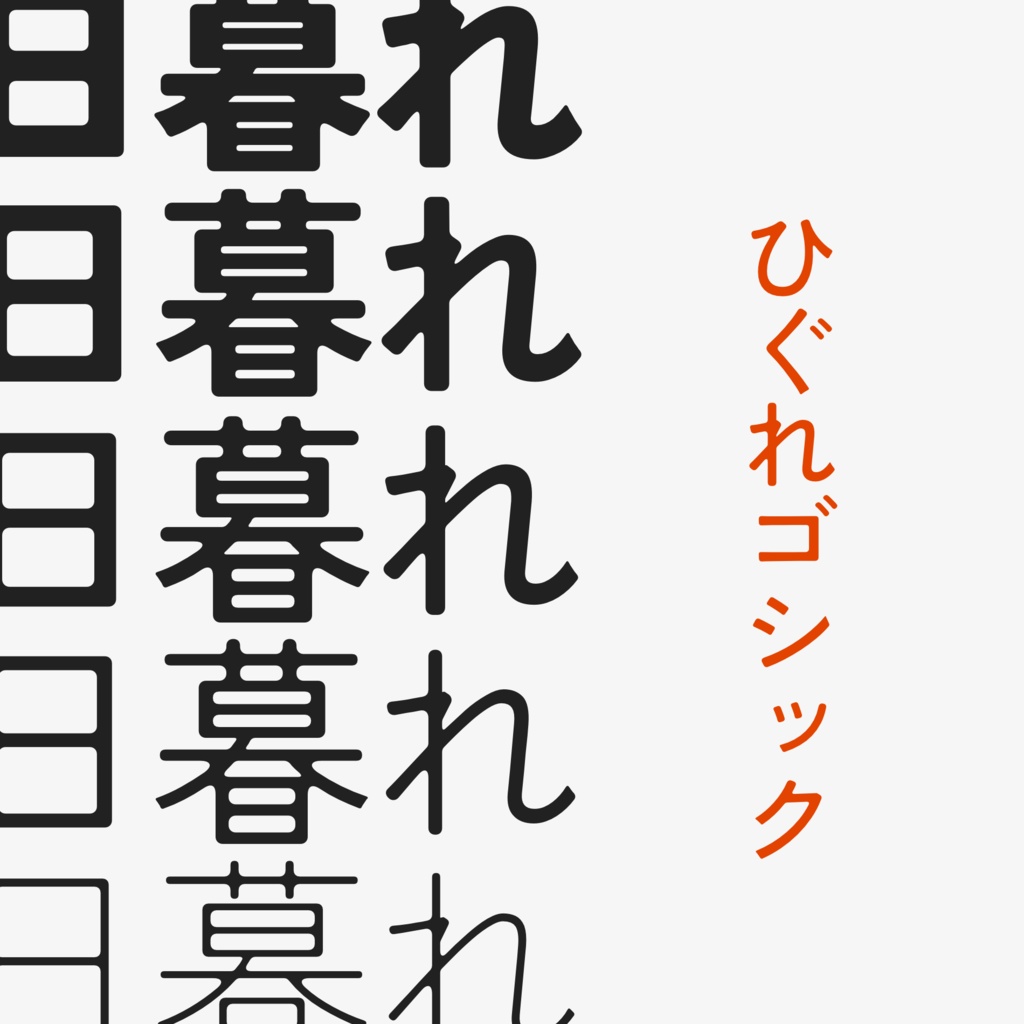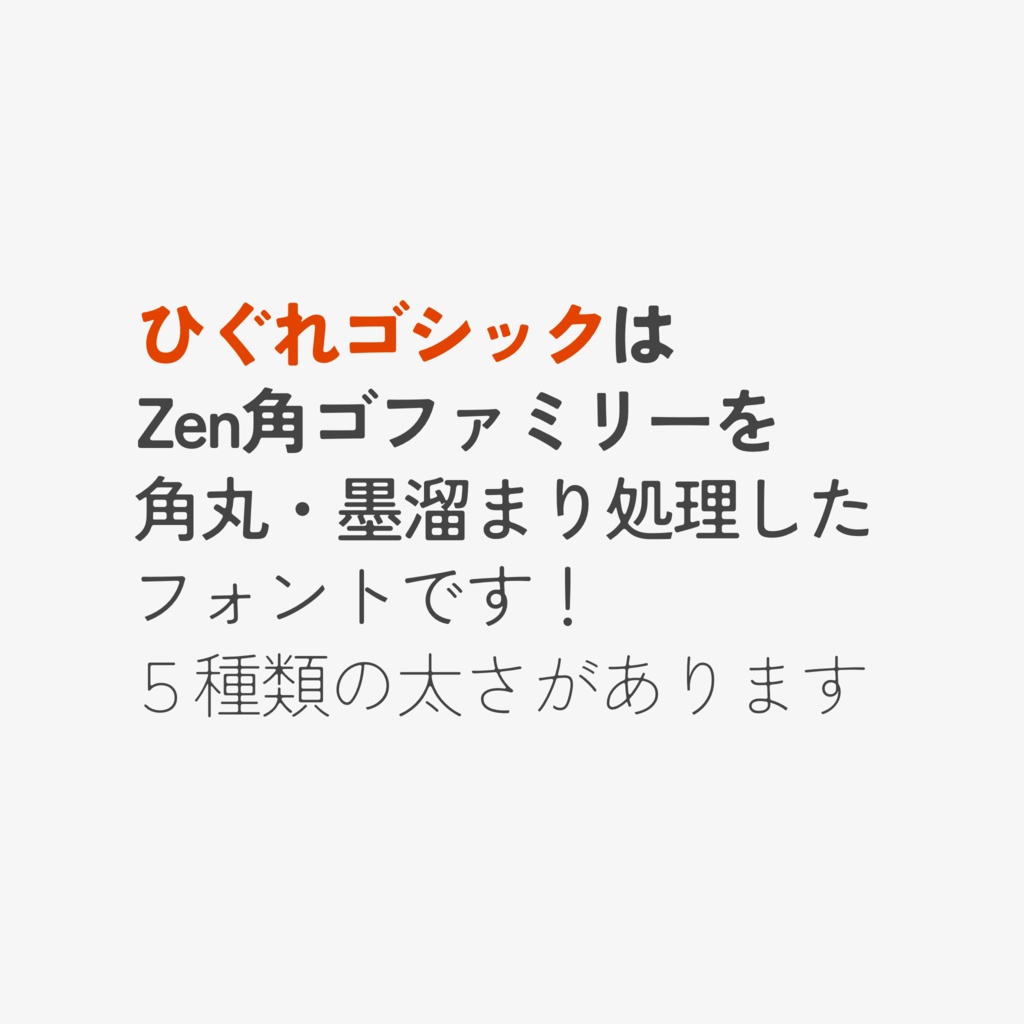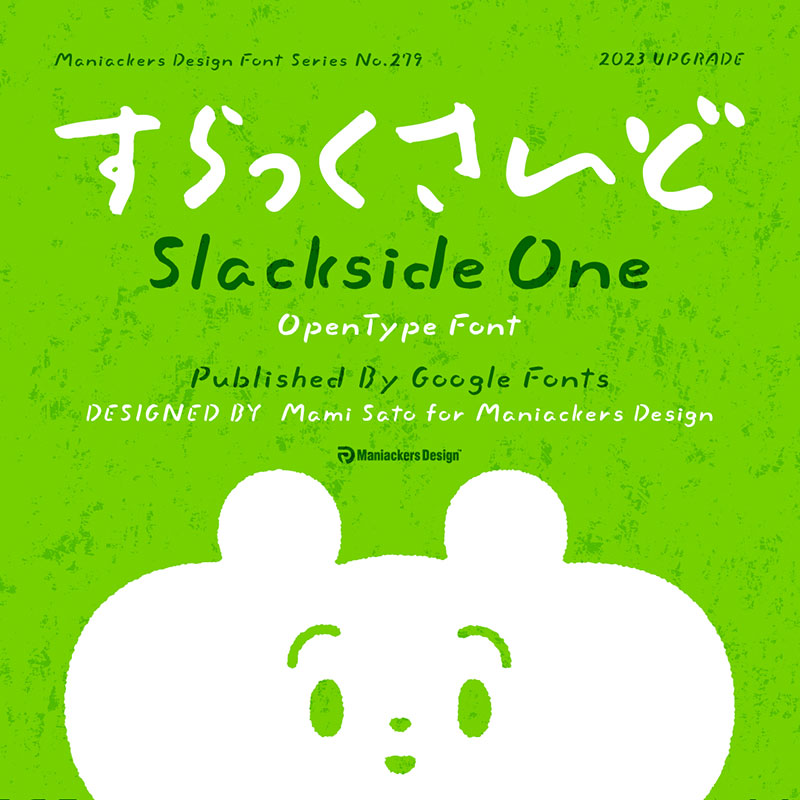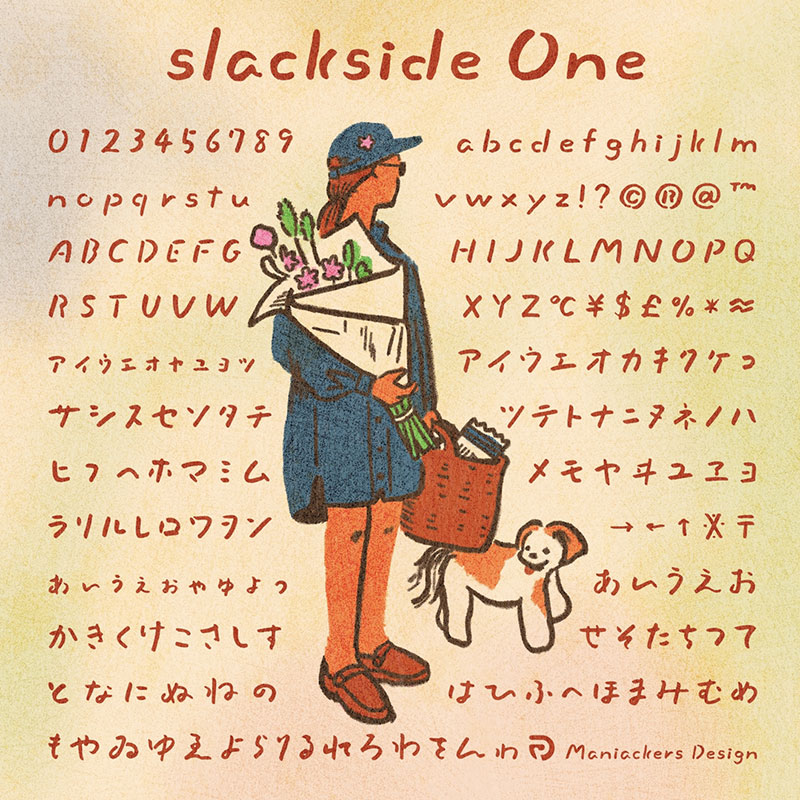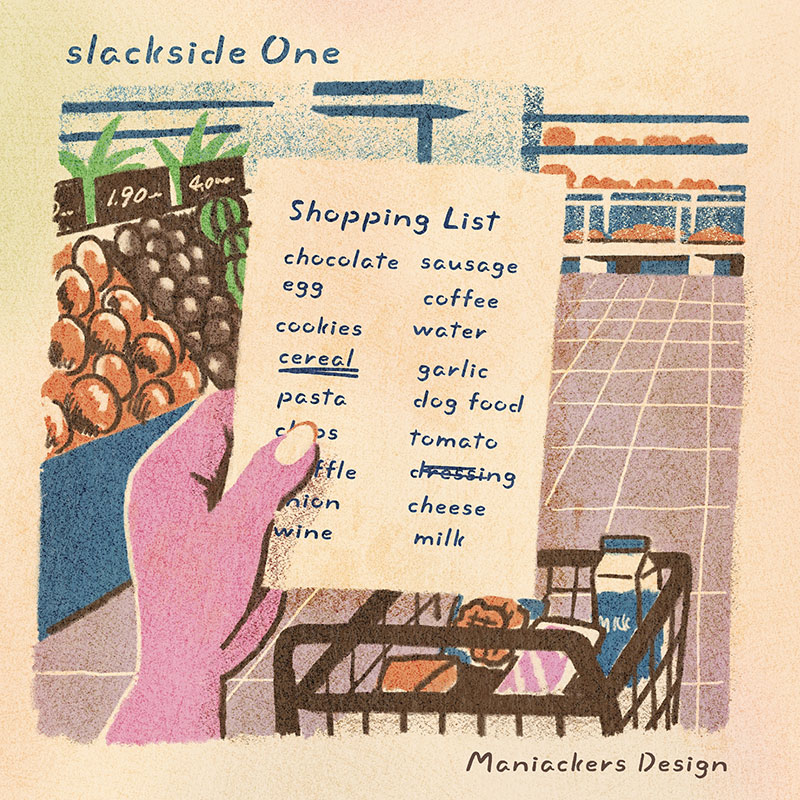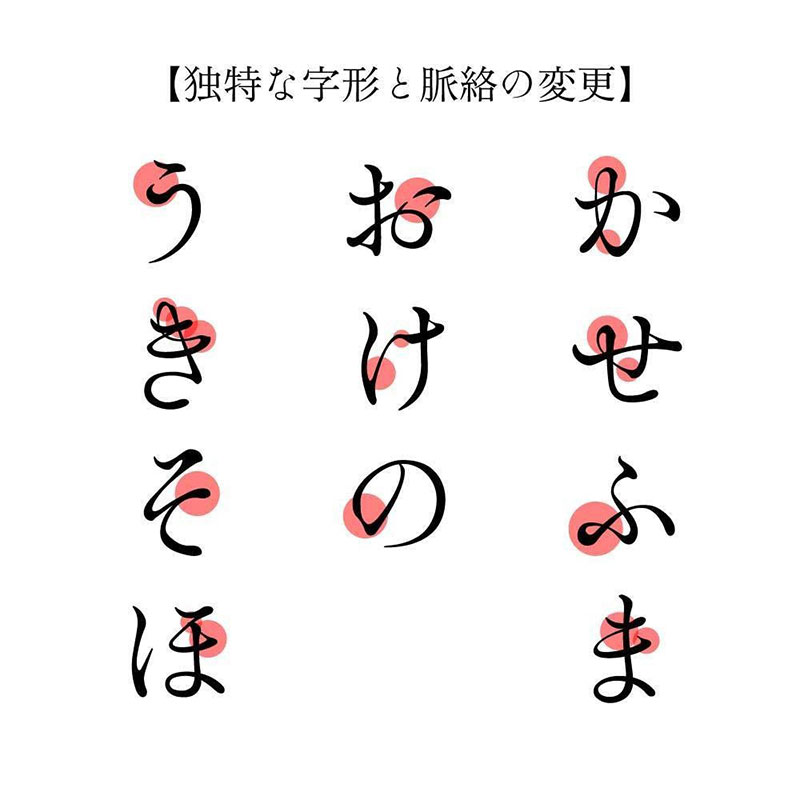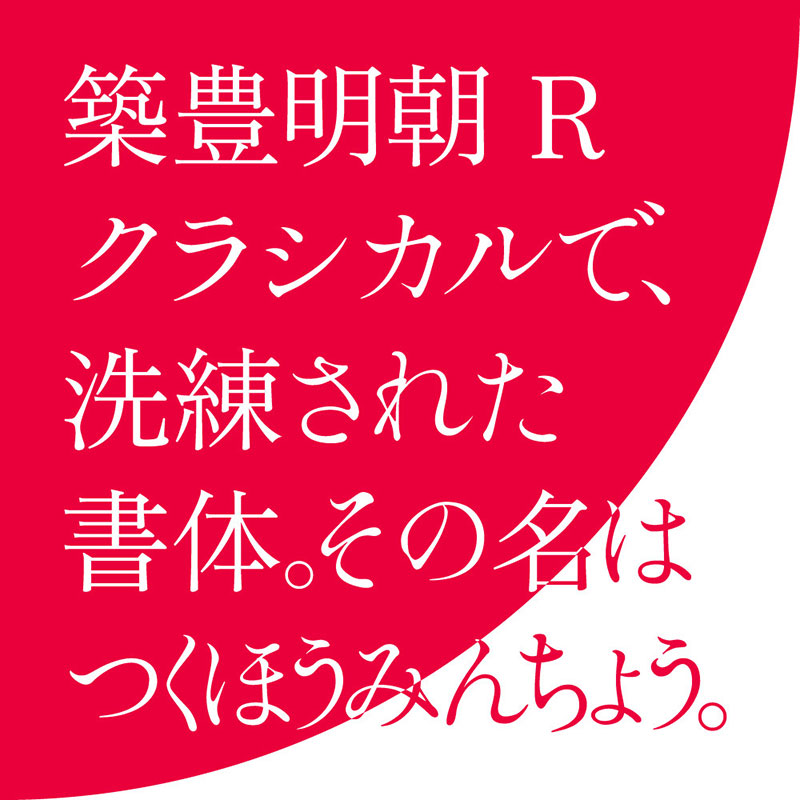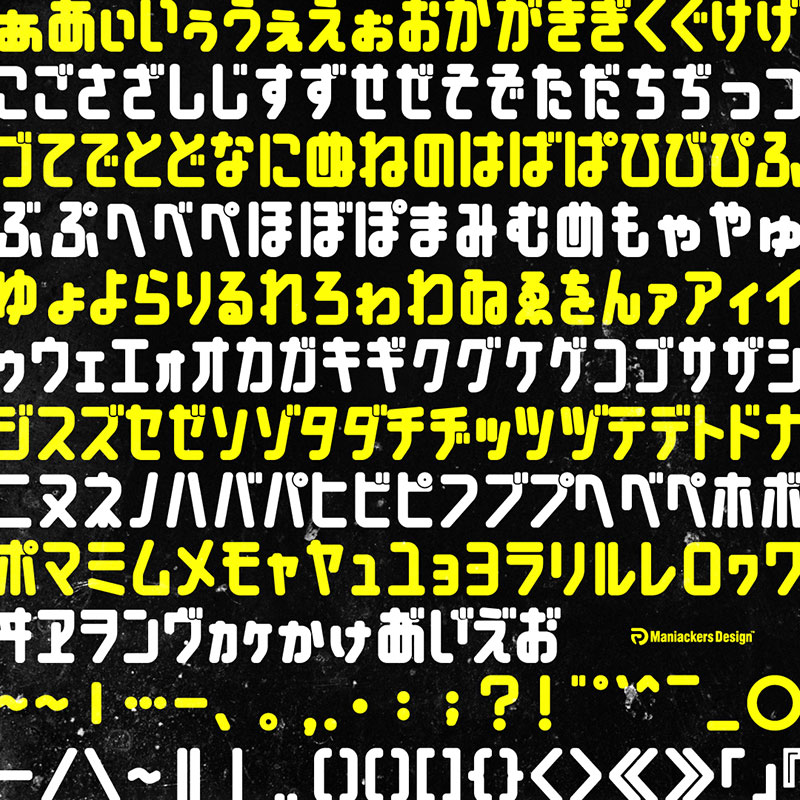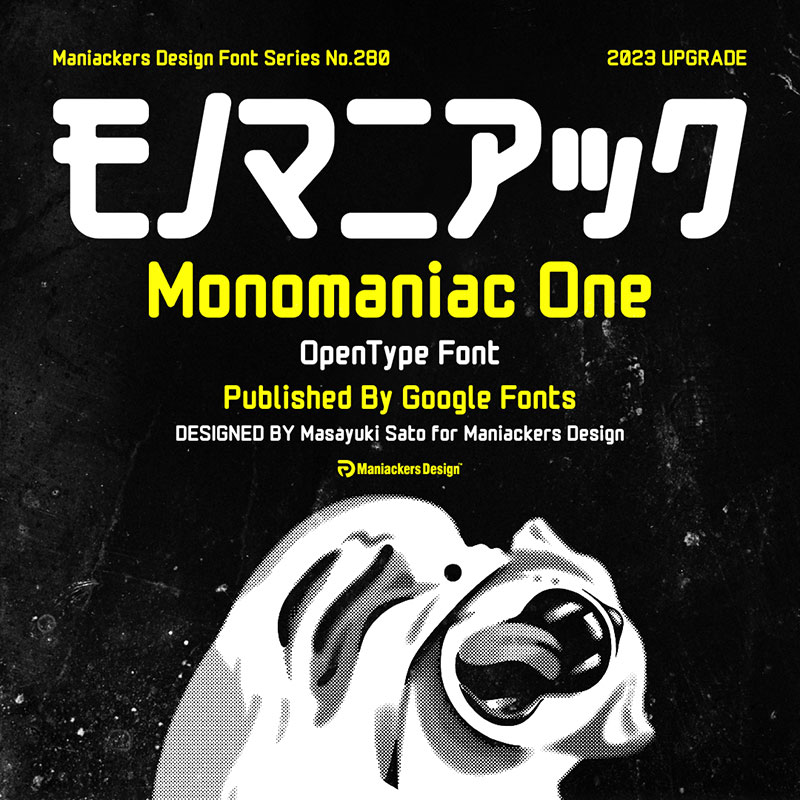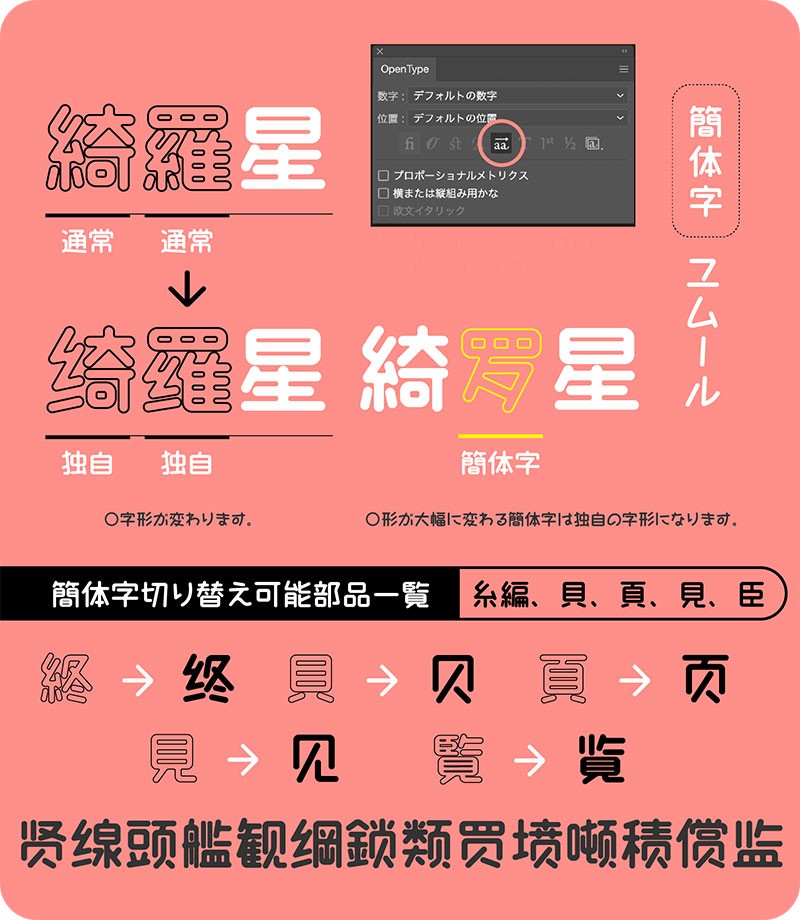
2023年上半年14款可商用日文字体合集
2023年上半年,可商用日本字体迎来了一波更新,这些新发布的日文字体汇聚了创新设计和美学追求,为广大设计师和字体爱好者带来了更多选择和灵感。从经典风格到现代感十足的设计,涵盖了多种应用场景,让文字传达更丰富的表达。每款字体附免商说明文本,可以放心使用,推荐收藏。
源暎ぽっぷる
一款用于漫画的免费字体,具有一定的手写 POP 风格,以 LINE Seed JP 为基础,具有宽大的字体和明亮的外观。
Monomaniac-One
一款粗体圆形哥特字体,所有角均为圆角。
築豊明朝│オールドスタイルかな書体
Slackside
一款粗犷的手写日文字体,包括平假名、片假名、符号和英文字母。
ひぐれゴシック
字体采用圆角处理,根据SIL开放字体许可证发布,包含五种不同的重量;该字体有多种尺寸可供选择。
つきみ丸ゴかな
一款带有笔触的圆形哥特字体。该字体适合竖排格式,有五种重量可供选择,您可以根据需要选择适合您设计风格的字重。
晩秋レトロミン
一种具有复古感的日文字体,适合用于标题而非正文的字体。
新レトロ丸ゴシック
该字体提供普通、中等和粗体三种字体易于使用,可用于从标题到正文的各种用途。
あおぼし
一款具有统一字母粗细和衬线的日语字体,具有清晰的线条和优美的曲线,展现了简洁、现代的风格。该字体非常适合在排版和设计中使用,可以为您的作品带来优美的视觉效果和协调的整体感。
ユムール
该字体制作于 2023 年,经过了很长一段时间的荒废。目前收录的汉字数量约为 3000 个,但二级汉字将在明年左右更新。
鉄路タイプフェイス
该字体具有铁路和机械的风格,包含片假名和少量汉字(73 个字符)。
金畫字(キンカクジ)
该字体支持垂直、水平和对角线(45°)方向,具有多种排版风格,可以满足不同设计需求。
しょかきペン体楷行草
一种款独特的钢笔字体,有楷書、行書和草書3种风格,可随意搭配。
Darumadrop One
一款富有风味和日本文化的手写字体,Darumadrop的意思是日本民间工艺品玩具 "Daruma otoshi"。该字体以民间工艺、传统工艺、昭和、禅宗、日本文化等为主题进行设计。